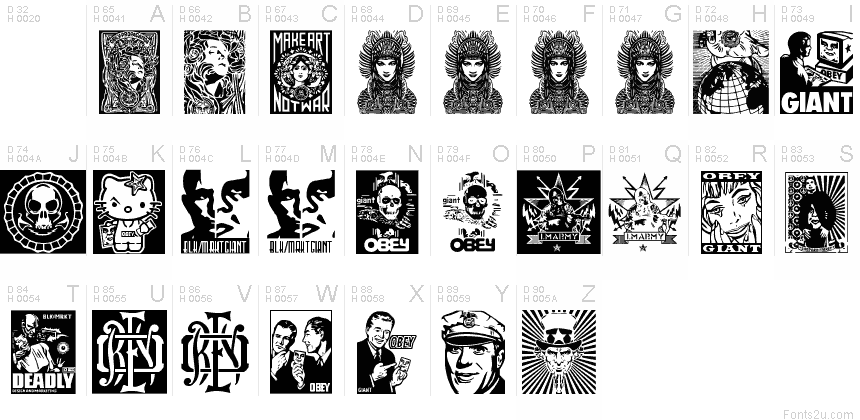
Obey Galleria autorstwa Bob is the Owl dla Metaphase Brothel Graphix to darmowy font dingbat z portretami, zakorzeniony w koncepcji Obey Giant autorstwa Shepard Fairey. Jego czarno-białe ilustracje łączą twarze, motywy czaszek, ostre cienie oraz gęste ornamenty liniowe. Efekt jest surowy i plakatowy.
Motywy sztuki ulicznej, sprzeciwu i portretów graficznych sprawiają, że symbole te świetnie sprawdzają się na gadżetach muzycznych, plakatach imprezowych oraz w materiałach redakcyjnych. W brandingu symboliczne twarze i zwarte znaki mogą posłużyć jako etykieta lub znak kampanii zamiast zwykłego liternictwa.